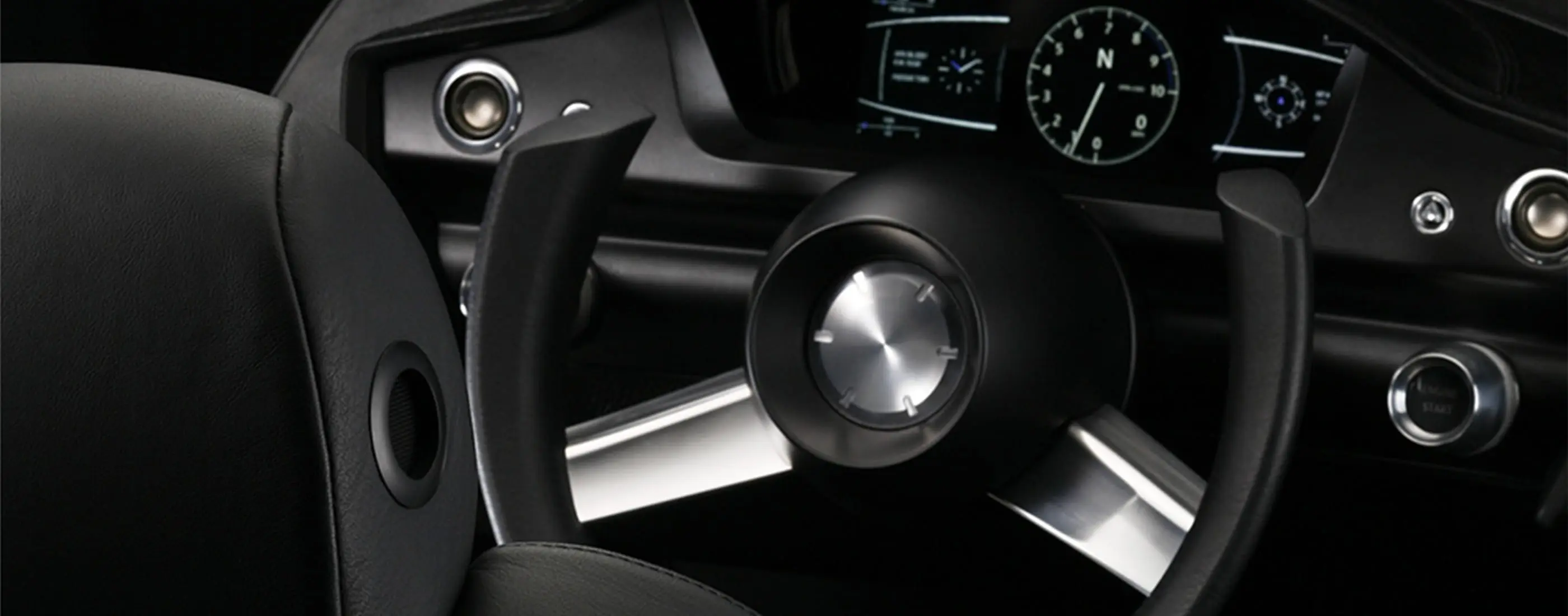
チラリと見る、印象が持続する
ドライバーズフォント
自動車メーカーにさまざまな機器を提供する大手サプライヤーである株式会社デンソー。そのデザイン部所属の梶田行宏氏はカーナビに表示される地図をより見やすいものへとデザインし直す必要性を感じていました。自動車の走行に応じてモニターには、さまざまな情報が浮かび上がっては消えていく。その分、文字やアイコンの置かれる状況は流動的で、従来のフォントとは「違う何か」を探っていました。
ドライバーのための新書体、それは究極の「チラ見」フォント
ドライバーの認知状況や身体感覚に根ざした自動車専用の書体をつくれないか、と考えた梶田氏から打診を受けたタイププロジェクトは共同で基礎研究を始めました。運転時に最優先されるのは安全性ですが、走行中、ドライバーは文字をきちんと読める状況に置かれているわけではなく、「拾い読み」したり、「チラ見」したりする程度。そのような状況にふさわしい文字とは何なのか。仮説・試作・検証の繰り返しは3年にもおよびました。初代バージョンでは、欧文と数字を中心に、走行状態によって変化する2種類の書体を公開しました。コンセプトはコンパクトな骨格と、メリハリのあるディテール。文字としてのバランスを考えた骨格を与えることに留意するとともに、 「チラ見」してもきっちりと印象に残るよう、細部の造形にはあえて強弱を与えたのです。
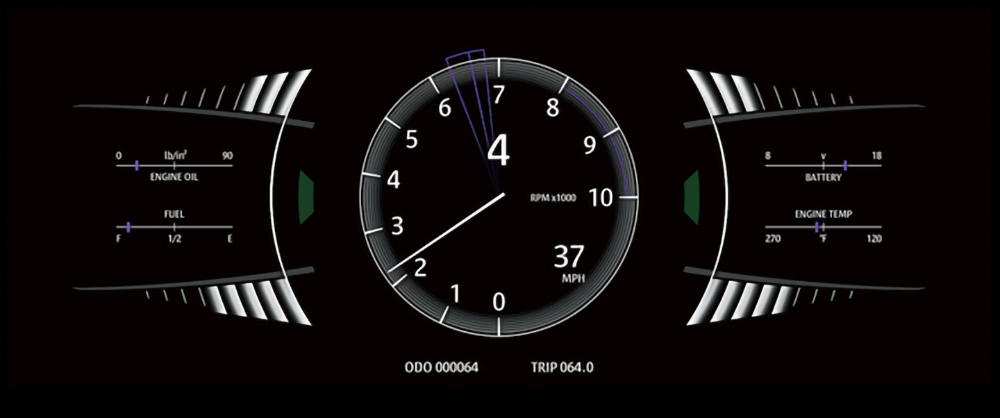
梶田氏は、ドライバーズ・フォントを単なる書体ではなく未来のインターフェースを構成する重要な要素と考えています。「課題を解決する最適な答えを導くには、文字を考えるだけでは不十分。 しかし、車室内のユーザーインターフェイスが取り組まなければならない課題に あえて文字を解決の糸口として提案することが、このプロジェクトの意義でもある。」
また、デザイン部長である伊藤義人氏は、「現在は、オーディオやカーナビなどの機能が飽和状態です。これらを一括で操るようなインターフェースができれば、 ドライバーズ・フォントの存在意義も高まるはず。この書体を使った自信作を、きちんと世に出したいと思っています」と開発の意義を説明しています。
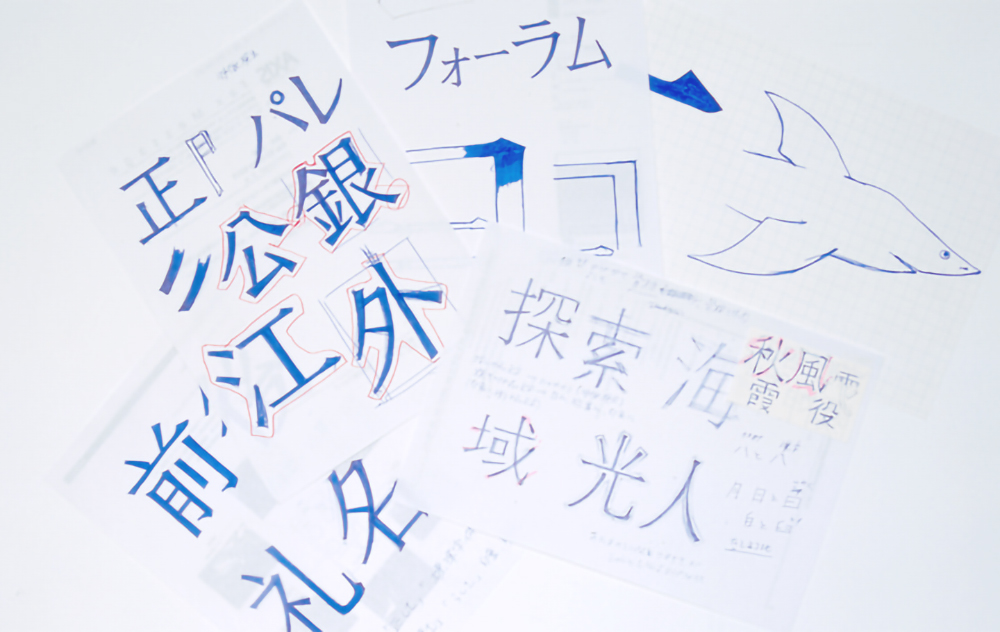
インターフェースを疾走する文字
ドライバーズ・フォントには、カーナビなどのデバイスに最適化した条件も加味される必要がありました。すなわち、見たいときにはしっかり見えて、それ以外のときはしっとりと地に馴染むような「心地よい異質感」を持った文字であること。さらに小さくてもはっきりと読め、内部がつぶれずに明るく見え、漢字・かな・欧文・数字が混在しても、自然なまとまりを持って読める文字であること。そのためにウエイトを変えても字幅や行幅が一定に保たれるように配慮しました。
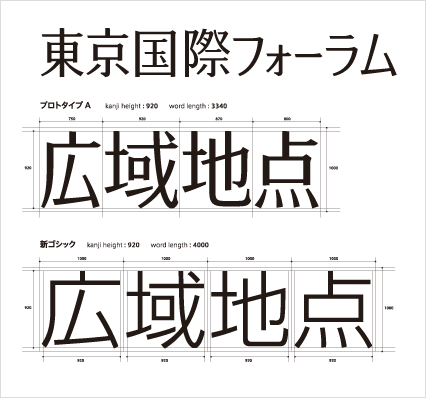
今や大半の制御が電子化されている自動車はデジタルフォントとの相性がよく、今まで以上に高解像度の液晶技術が一般化すれば、文字の精度に対する要請も増してくるでしょう。これからの自動車は、情報機能を満載した移動空間として進化するに違いありません。ドライバーズ・フォントは、自動車大国日本が世界に提案できる「新製品」となり得るかもしれないのです。
さらにドライバーズ・フォントは、自動車という枠組みにとどまらず「移動体としての人間」のためのフォントとしての進化を遂げる可能性をも含んでいます。インターフェースを疾走する文字。国内初の車載専用フォントであるドライバーズ・フォントの開発はこれからも続きます。